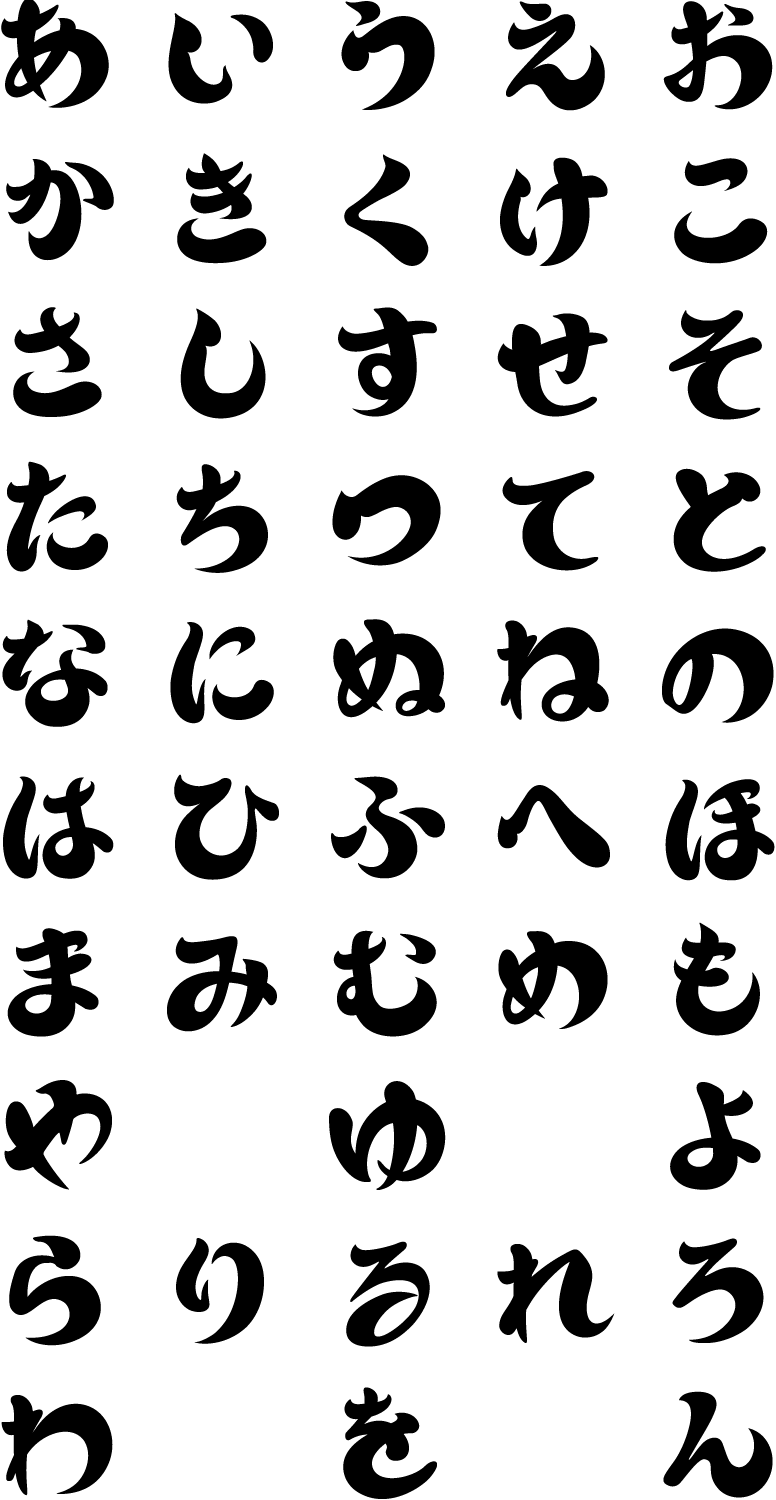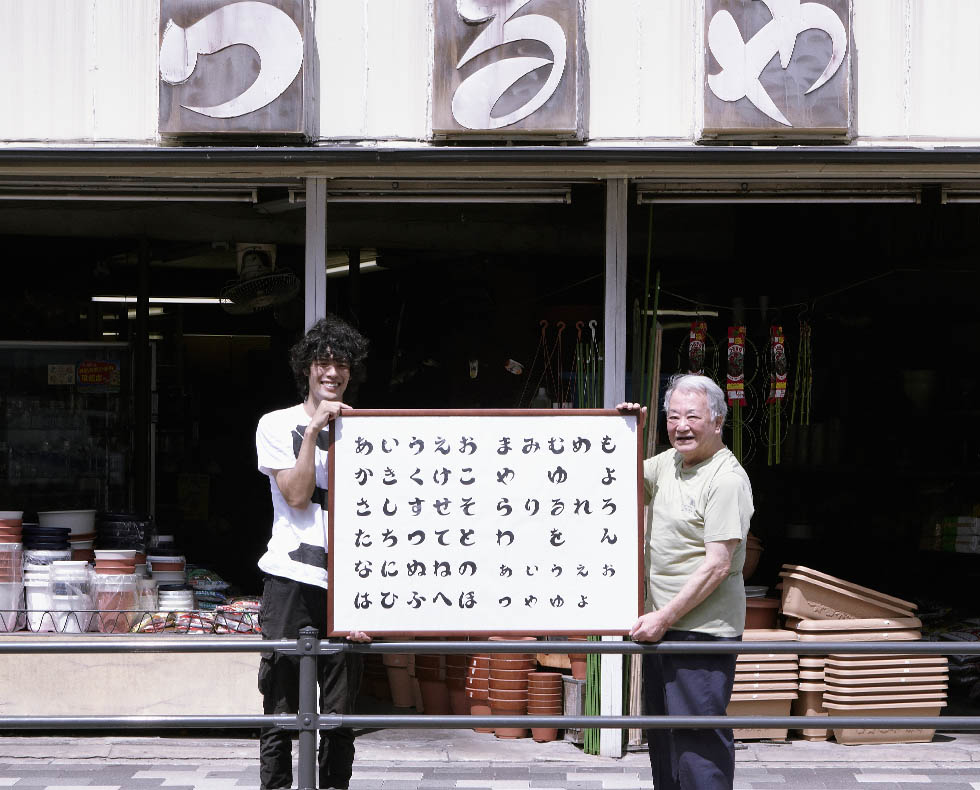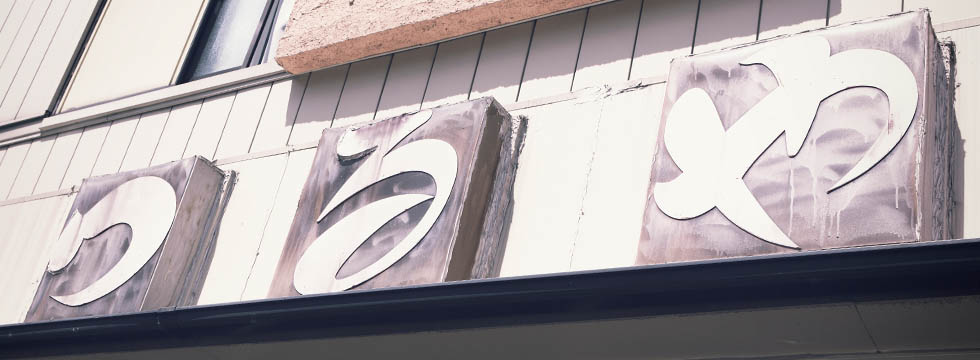
筆の勢いに任せ、手の赴くまま書いたかのような文字である。書き手の体温が、眼球から視神経にかけてダイレクトに流れ込んで来る、そういう書体である。
「つるや陶器」は戦後、うるし製品と中心としたお祝いのための品物の小売業としてスタートした。現在は陶磁器中心のお店になっている。「つるや」という屋号はお祝いの品物を扱う商店なので縁起のいい名前をということで名付けたそうだ。「看板の書体はおやじが作ったんじゃないかな?うちのおやじは絵を描いたり、作品つくるのが趣味だったんだよ。一度でよしとけばいいのに、二度も個展やって、二度目は近所の鼻つまみもんだったよ〜まったく…アハハ!」と息子で二代目の井藤さんは楽しそうに語る。看板の文字はもともと真っ赤だったそう。当時出始めたばかりだったプラスチック制だったが、アーケードがなくなるとともに日に焼けて現在の色になったという。真っ赤な時の看板も見てみたいが、今の状態も趣があって非常に魅力的だ。
“Tsuruya Pottery Store” started as a retailer of products of Urushi and other goods for celebrations after World War II. Today, the store focuses on ceramics. The name “Tsuruya” was chosen for getting good fortune because they handled festive goods. “The typeface on the signboard was probably created by my father. My father enjoyed drawing pictures and making artwork as a hobby. He held his own exhibition but he should have done it only once, but he did it twice. So the second time he was made a fool of the neighborhood...hahaha!” Mr.Ido the second generation says happily. He said the letters on the signboard were initially bright red. It was plastic signs that were up to date at the time, but as the arcades disappeared, they were fading by the sun and became the color like today. It would be interesting to see it when was bright red, however, the current sign is also very charming and atmospheric.